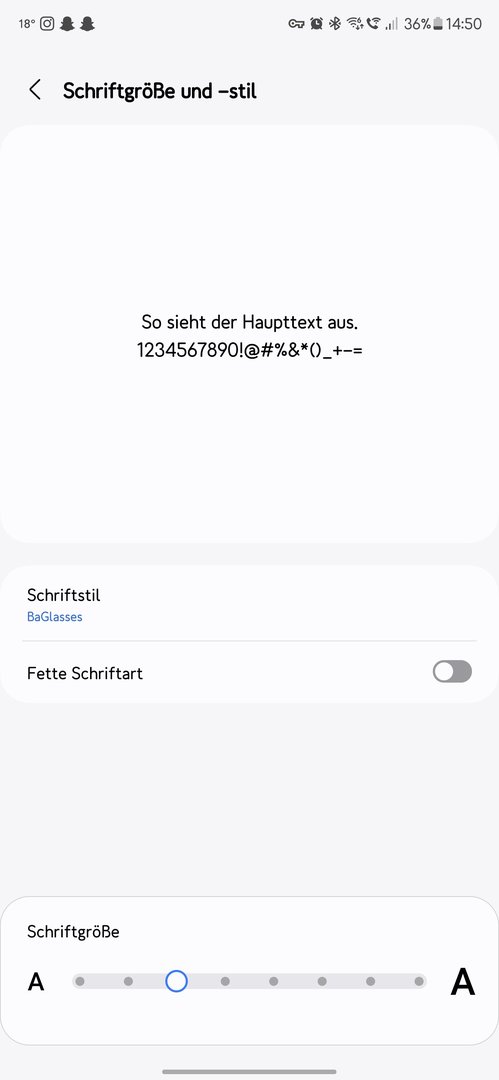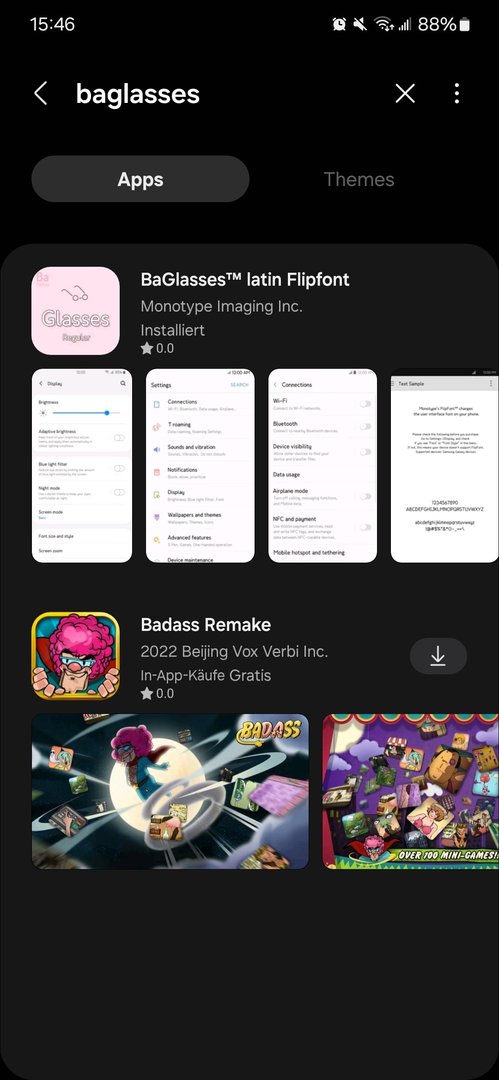
Welche Schriftart nutzt ihr?
habe seit gestern das tolle Smartphone und möchte eine schöne Schriftart installieren. Hab zwar eine andere, als die Standard, aber das sieht echt blöd aus auf der Tastatur. Bei Swiftkey z.B. ist die Schrift viel zu klein.
Welche Schriftart benutzt ihr und wo kann ich, wenn mir eine gefällt, laden/kaufen?
Ich habe sehr lange diese hier genutzt:
Habe aber gestern mich entschieden mal wieder bisschen anzupassen und eine neue rauszusuchen für ein bisschen Feinschliff und bin bisher mit dieser hier auch sehr zufrieden:
Am Ende des Tages darf die Lesbarkeit nicht leiden.
gibt einige optisch schöne Schriftarten, die m. M. n. aber die Lesbarkeit verschlechtern.
ich nutze Gothic Bild.
Ist das intern auf dem S24?
Die sieht richtig gut aus👍
Keine Sorge, man kann mit jeder Schriftart auch Deutsch schreiben 😉
Aber hat keine Umlaute?
@Rieselrass Selbstverständlich hat die Schriftart auch Umlaute :D